「2021年东京TDC展」
2021年东京TDC展览于4月1日开幕,展出了今年度的获奖及入围作品。而在4月2日的东京TDC赏线上颁奖典礼上,东京TDC连线了世界各地的获奖者,对本年得奖作品进行嘉赏。来自广州的设计师刘钊及其团队another design凭借其「讲什么-广州语言观察展」作品,获得了本年Tokyo TDC大奖。
刘钊
「讲什么-广州语言观察展」是以观察者的方式和视觉去呈现粤语生猛鲜活能量的一次内容探索。从中英数字谐音、绕口令、语气助词、“鸡”的俚语、“菜名”、童谣、叠词这7个维度出发,这个项目并不止步于对文字与语言的呈现,而是通过激活粤语的独特韵律,将广州的街头文化进行了可感的视觉转化。而这个获奖视频,就是对整个内容的提炼与总结。
当准备在广州落座的时候,以街头与市井文化为其品牌形象的超级文和友联合another design策划了一次对粤语文化进行观察与解构的展览活动。广州超级文和友坐落在商业区中心,其空间的概念是老广州的场景还原。
在对语言,这个承载了当地文化与记忆的载体,进行解构与重现的基础上,这次展览内容和作品尝试重新概括广州鲜活、包容、生猛的城市生态。语言与街头美食这两种粤文化代表,在这次展览作品与空间中,通过视觉策划得到了淋漓尽致的融合与展现。
2021年东京TDC线上颁奖现场
在这当中流露的上世纪80年代广州的街市人情与烟火气息,也是最为打动东京TDC主席及评委浅叶克己的地方。浅叶克己在4月3日的获奖作品点评分享中谈到,虽然他不太懂粤语,但能通过这次作品感受到粤语的魅力。“每次去餐厅,菜单上的汉字都会引起我的注意,我不太懂粤语,但当我观察它时,这不会太影响我对汉字的理解。”
浅叶先生强调,观察对设计师来说非常重要,这次对粤语的观察所体现的70、80年代的充满怀旧气息的字体氛围让他印象很深刻。“这些字体看起来并不特别,但可以同时使用这么多日常字体是非常好的事情。用这样日常的字体拿到TDC大奖,也是一次挑战。”
2021年东京TDC线上分享中,浅叶克己在点评作品
在这个项目中,刘钊与团队负责的不仅是展览视觉设计;从形式到内容的输出,甚至包括展览标题,都是由他们自己来组织产生,是内容与形式更为系统的一次连接。如此完整的一次创作,对刘钊来说,是他在文化项目策划上的再一次突破与提升。
从文和友谈文化项目,对概念的诠释可以超越美丑
“很多时候,大家过于注重去思考客户想要什么和喜欢什么,而没有去想这个项目是否或怎样可以产生更多反响。”
一直以来,在文化项目深耕多年的刘钊从不满足于仅仅是形式上的视觉输出。在他看来,对概念的重视与透彻的解析,再结合形式的统一,才是对一个文化项目的真正拆解与再现。
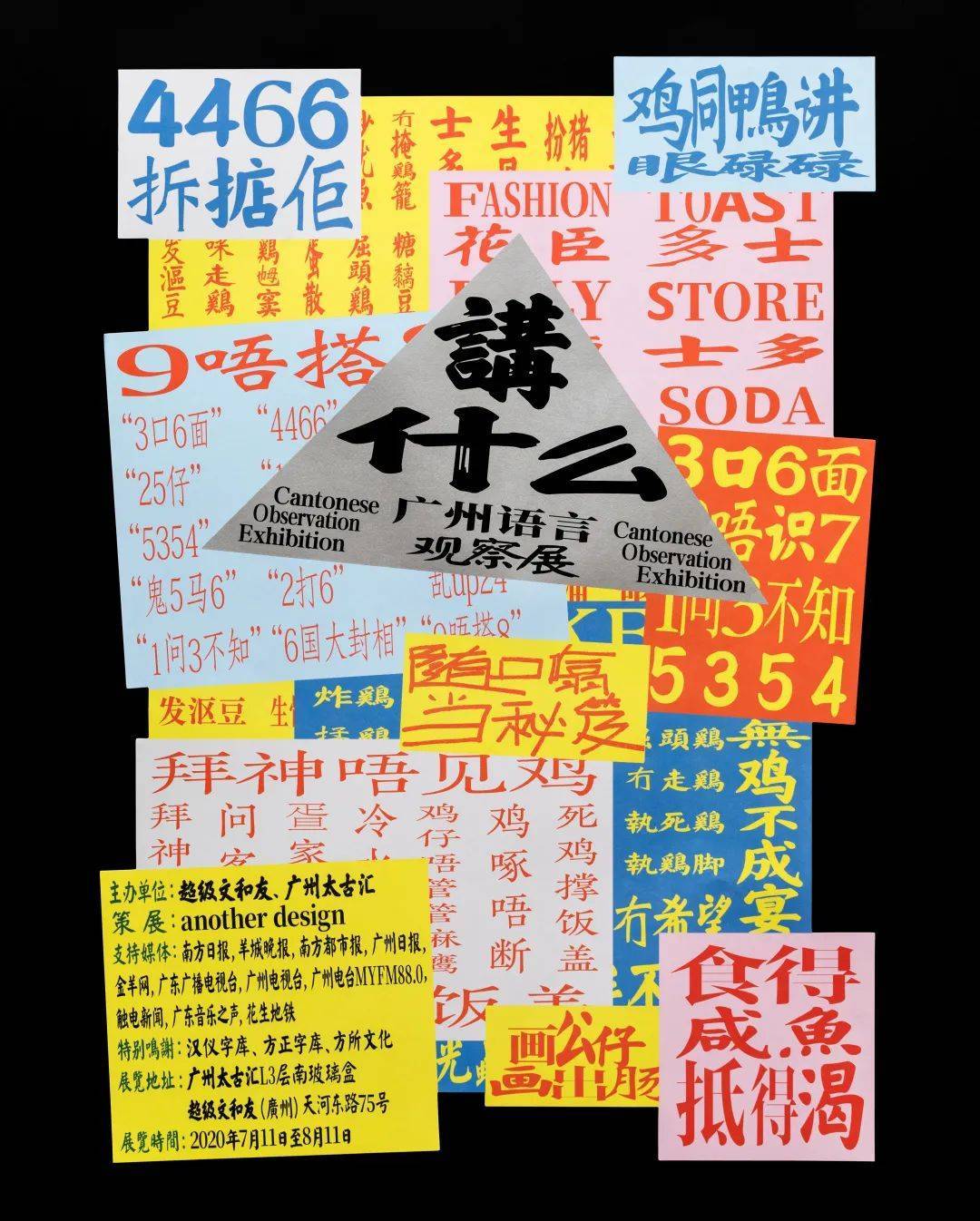
「讲什么-广州语言观察展」海报
不少人在进行文化项目设计的时候,往往过于在意字体、图形等本身的设计,其实背后概念并不强,在这样的情况下,创作的字体也不会足够具备煽动性。文化项目更多的是在解题,而过于注重表面形式的话,一不小心就会形成流水帐一样的局面。
“很多时候,大家过于注重去思考客户想要什么和喜欢什么,而没有去想这个项目是否或怎样可以产生更多反响。”
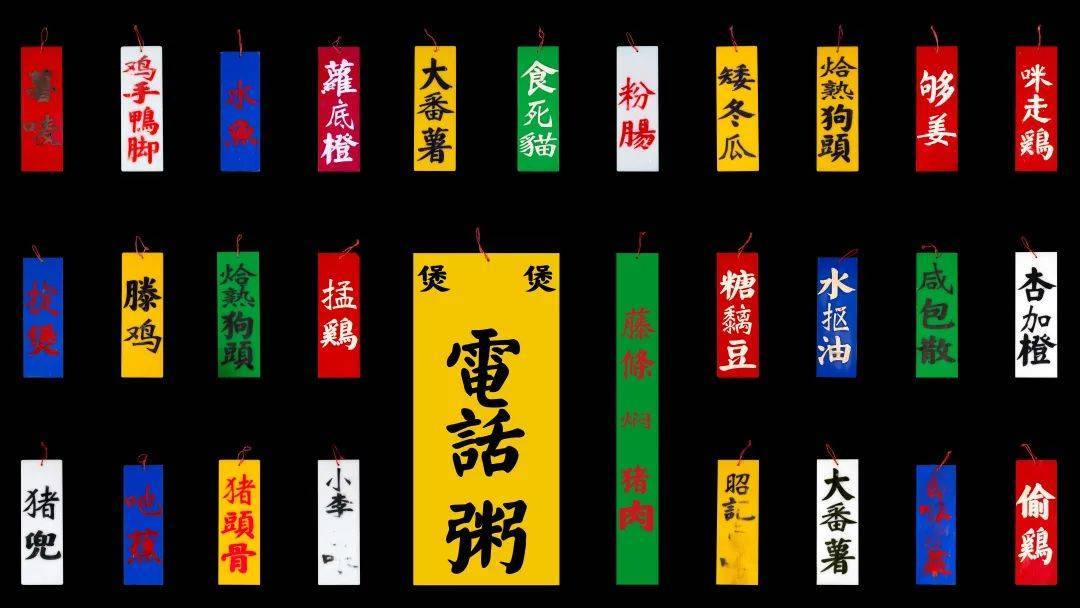
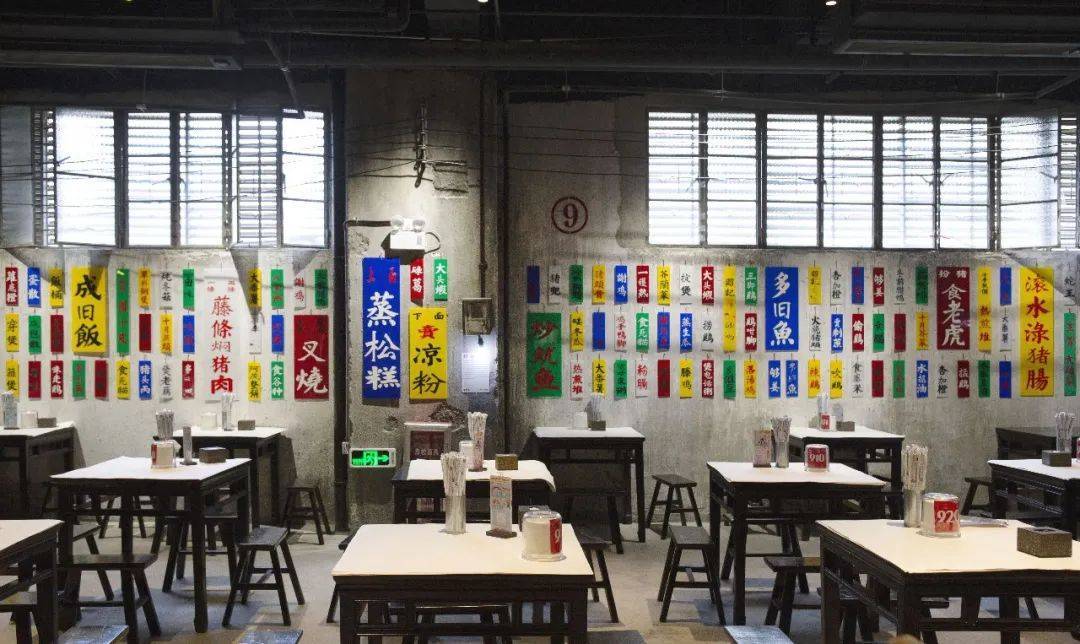
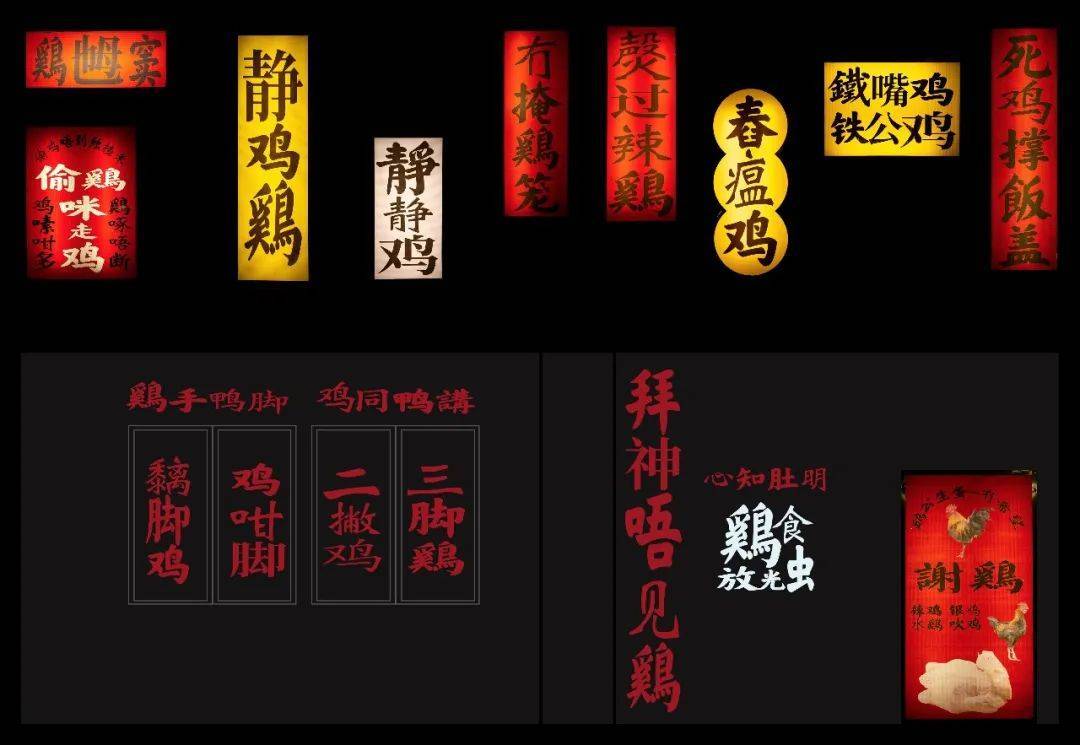
刘钊在接洽项目的时候,一直更注重创作与策划的思维。在他看来,如果只停留在设计本身,其实只是在响应客户的需求,然后再进行视觉呈现与美化而已。而他则更多的是去创造一套逻辑,在客户原有的需求以外构建另外一层高于客户的需求,然后再与客户碰撞调和。
「讲什么-广州语言观察展」
与超级文和友的合作也是这样一个案例。以往许多时候,刘钊与团队是为艺术家负责,而这次语言展是为大众负责。在受众转变的情况下,他们主动参与到项目的定调,去把控更多的话语权。在这次合作中,他们与客户是在概念上共同合作的状态。在这次定调中,基于文和友原本街头与市井的调性,刘钊将展览基调落在“俗”这一点上,去用世俗的各种面向去展示粤语鲜活的生命力。
「讲什么-广州语言观察展」
在设计形式的选择上,刘钊直接将最市井日常的东西带到现场:“你在城中村走一圈所能看到的东西,可能我们都会想着怎么把那些东西用到我们的设计上面。”菜牌、灯箱、发廊灯、招租式的广告牌、信报箱、汗衫……刘钊与团队将他们在平日所观察到的细琐场景都收集起来,用最直观的方式给观者以沉浸式的感受。所以在最终的呈现中,能让大家感受到在这当中不只是视觉形式的观感,而是从视觉、内容、形式去综合体验粤语本土文化的魅力。
「讲什么-广州语言观察展」
在「讲什么-广州语言观察展」这个项目中,刘钊的角色更像是策展人或者导演。正如浅叶克己所言,这里使用的字体很“日常”,但也正是这些日常所组合出来的氛围,体现出超越平面设计的感染力。刘钊所着眼的不是美丑,而是无论怎样的设计形态,都能通过策划为自己所用。
「讲什么-广州语言观察展」可以说是刘钊在过去对概念的突破与策划思维的积累的一次充分的体现。而这种从不轻易满足、从设计跳跃到策划的转变,其实一直潜藏在刘钊并不安分的设计历程中。
从深圳开始,埋下了不安份的创作欲望:
“尝过了突破的甜头,再也不会忘记要持续突破这件事。”
从2007年起的那四年,是刘钊奠定设计观念与行事风格的时期。当时的深圳有GDC07、X展、华侨城创意节、字运动、中岛英树展览等等各式各样的展览活动,整个城市的设计文化氛围特别浓厚, “那时候见识了很多大师的作品,许多设计都是不敢想象的。每天都跟打了鸡血一样,很兴奋。”
看过与没看过,视野上的开拓对一个人的成长与认识来说,有着至关重要的奠基意义。那时候,刘钊加入了黑一烊主理的工作室SenseTeam。黑一烊的引导与启蒙,以及当时的许多前沿行业活动,都对刚入行的刘钊在设计的认知上造成一次又一次的冲击。
2011年,黑一烊与刘钊
“那是一种开悟的感觉,当你知道突破那种感觉是怎样的时候,其实接下来整个职业生涯都不会忘记再次突破这件事情。”
这样的冲击对刘钊来说是影响深远的,对平面设计的理解与认识,在这个时候就已经在他心中划下了一道很高的基准。这样敢想敢玩的种子在刘钊心里埋下以后,他在接下来的职业道路中就再也难以安守本分。在商业公司里无法呆过两个月,是因为刘钊越来越不能忍受不需要过多思考和无法打动自己的项目。他对突破的执着逐渐多于服务和满足别人,“我对自己的定位不再安于是设计师,而是总想去创作、策划一些东西。”
这种对突破的渴望,也同样体现在他对自己不断进步的追求上。在看到「社会能量」展览上卡尔·马藤斯的作品,刘钊再次被平面设计的深度所撼动。在这之后,他前去广州加入王序工作室,也在那里认识了之后职业生涯的重要搭档詹火德。与詹火德所组成的设计工作室another design,承载了刘钊设计事业的快速发展与对创作突破的不断探索。
与another design一起从设计到策划,
从“拙”劲到前沿技术
“在文化项目上想做出点事,某种程度上是要有觉悟的。”
刘钊与詹火德的相识,对彼此而言都可以说十分幸运。他们对设计都有着相似的叛逆心态,从此在以后的许多抉择关头,有了这种并肩上的相互鼓励,刘钊就更大胆地实现着内心一个个设计玩法。
刘钊和詹火德
another design团队
在创立工作室之际,刘钊在香港翻到一本叫《anotherman》的杂志,那一瞬间他就觉得“another(另一个)”这个词特别符合自己对未来设计创作的定位和理解。之前所开拓的视野与内心的不安分,让刘钊在当时就暗下决心要去做一些非平面和非传统的设计。
“‘另一个’这个词有站在不同的角度、不同的对立面去思考问题这样的意味。我看到这个词的时候就特别兴奋,火德也非常认可这个词。我们希望我们未来团队所做的设计也是不随潮流,而且可以处于不停提出质疑、一直保持独立思考这样的状态。” 这样的定位与刘钊本来的性格也十分吻合,“我希望永远在强调‘另一个’,我就永远是这样一个不太合群、不太合适的状态,甚至有点逆潮流的意思。”
another design工作室与刘钊的办公室
another design的第一个项目「积极空间」已经展现了刘钊蠢蠢欲动去玩转设计的念头,以及初见他以后在不同维度上进行设计突破的探索。策展人将积极空间比作活跃在中国当下的小型自我组织的艺术机构。在这个综合的空间与平面的项目里,刘钊与团队用不同的架子焊成了一个个通道,将它们作为插件置于这个空间。
这个插件不只是填充空白,而是在不能在墙上打钉的情况下,起到了连接与激活空间的作用。谈及团队第一个项目,刘钊依然十分兴奋,因为这是他们两个不安分的人第一次成功的尝试,“它释放了我们不安分的心,从此我们就鼓励自己继续这样走下去。”
2014年 「积极空间」展览
2014年的深圳双年双城展(简称深双)威尼斯的推广展上,刘钊再次不想拘泥于只用平面设计去输出内容。他与火德一人拿着投影仪,一人拿着摄像拍照,通过投影的画面去实现超越二维的理念,在不改动深双LOGO的情况下“改动”了LOGO。投影的做法源于他们希望用电影去串联两座城市的概念,这也是刘钊自己对这次推广活动所去联想产生的理解。“这个做法其实不是去给别人他们想要的东西,而是我们自己去深挖项目概念,去感受我觉得这件事情应该怎样做。”
2014年「深港双城双年展」
如果说之前的项目是刘钊在形式与解题方面的突破,接下来2015的深双、无乐不作与时间之风就是他和团队在媒介与内容上的探索,以及如何在它们的关系中间再去突出观念。
在2015的深双中,相比于直接创造一个新的东西,刘钊与团队借用了具有刻板印象的传统媒介——报纸,在旧媒介的再利用上去打破原有的认知与呼应“城市原点”这个展览主题。媒介本身虽然也可以被归类在形式里,但它对于传统理解里的形式是有所突破的,通过借用现成的东西,他们对观念与传递概念进行了更纯粹的探讨。
刘庆元与刘钊合作作品
在去年末,他参选了深圳市平面设计协会的理事选举,成为了新一届的深平协副主席。“今年参选深平协,其实我会希望看看能回去为行业做点什么。”
从事文化项目设计多年,关注到设计的社会与文化属性对刘钊来说是自然而然的事情。“现在不少人做设计,是为了做设计而做设计。有时候创作了一些花里胡哨的东西,但其实背后缺少一个核心,没有想要表达的概念或者也没有在某种形式上进行了探索。在本质上,他们还是停留在一个个人的层面去做设计,没有拓宽到更广阔的维度去进行钻研。其实往往到了后面,更多的人文、社会的问题就会涌现出来,即是说设计到底能改变什么?”
所以现在刘钊在做文化项目的时候,更渴望能够带入一些社会性的思考。在概念与技术同步并进的同时,他期许可以辐射出更多社会能量。“哪怕只是一些很小的展览和活动,我都希望可以先去激活这个地区的设计力量,让更多人关注到平面设计。”
这些年一路走来,刘钊可以说从未安于自己原来所处的位置,并且一直在努力跳出自己的舒适区。这种刻在骨子里的不安分与躁动,相信会让他在未来持续迸发出变化多端的能量。